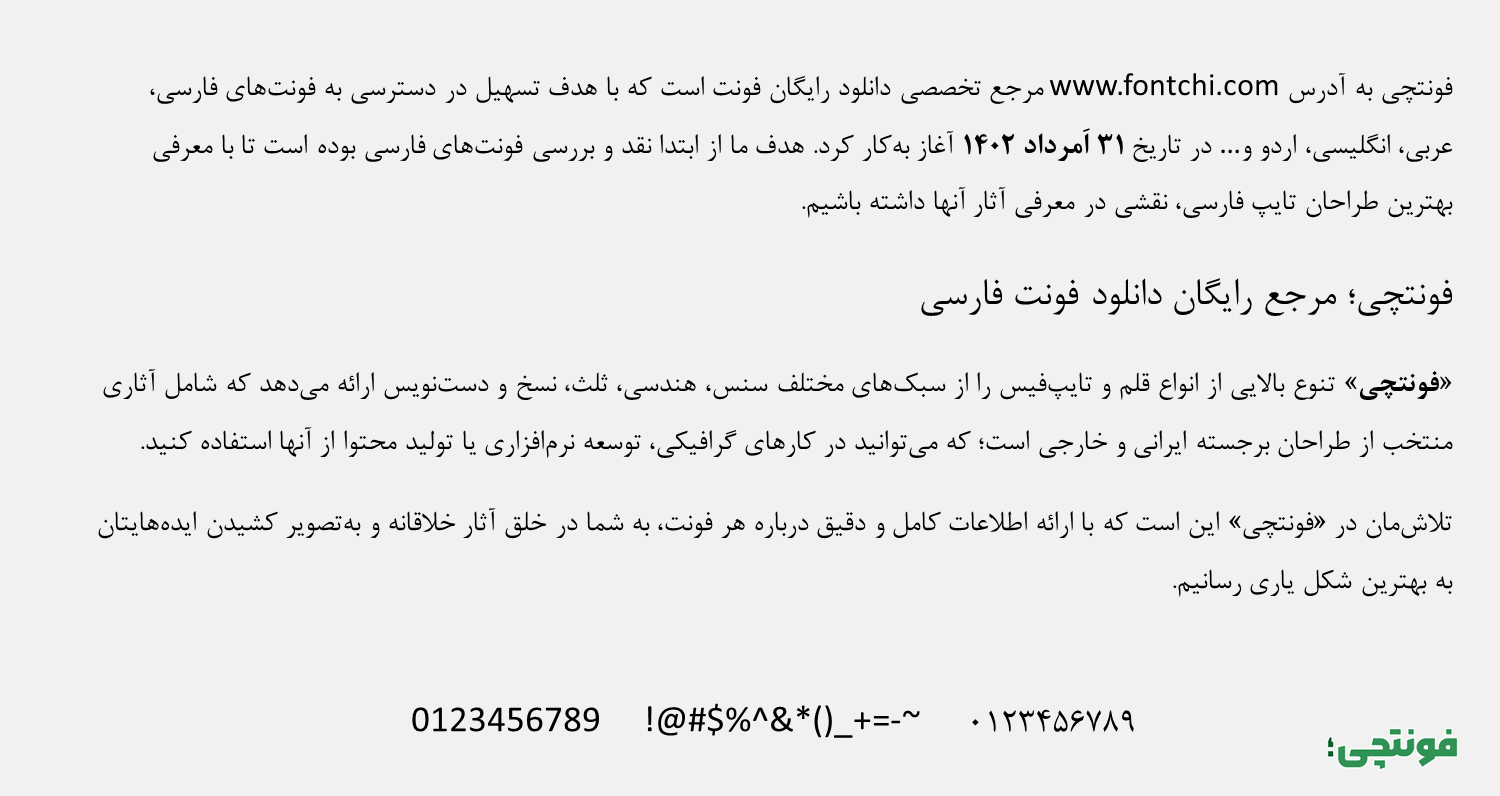
فونت بی نازنین (B Nazanin)
فونت بی نازنین یا فونت ب نازنین (به انگلیسی: B Nazanin) یکی دیگر از فونتهای طراحی شده توسط برنا رایانه است که ساخت آن به دهه ۷۰ برمیگردد. این فونت با خط نسخ طراحی شده که بیشتر در ادارات و سازمانها به عنوان فونت رسمی و اداری مورد استفاده قرار میگیرد. در ادامه این نوشته به لینک دانلود فونت بی نازنین رایگان دسترسی خواهید داشت.
این فونت دارای یک وزن معمولی نرمال است که از دو حالت Regular و Bold پشتیبانی میکند. فونت B Nazanin آخرین آپدیت خود را در سال ۱۳۷۹ دریافت کرده است که نسخه ۲.۰۱ این قلم میباشد.
فونتهای سری بی که فونت B nazanin یکی از محبوبترین آنها است، جزو اولین فونتهای فارسی هستند. این فونتها که در دههای که هنوز خبری از گوشیهای هوشمند نبود و در خانه معدود افراد ایرانی میشد سیستم کامپیوتری یافت طراحی و تولید شدند.
ادارات، سازمانها، شرکتها، مراکز علمی و انتشارات از این فونت بیشترین استفاده را دارند؛ بهطوریکه روزنامهها و مجلات برای متن بدنه اصلی خود یا در نامه نگاریهای اداری از این فونت استفاده میشود. این فونت به قدری امروزه رواج یافته که در پروژههای دانشجویی برخی اساتید استفاده آن را الزامی کردهاند.
در تصویر زیر پیشنمایش این فونت را مشاهده میکنید که حالتهای فارسی، انگلیسی، اعداد فارسی، کاراکترهای خاص و نسخه بولد شده آن را نشان میدهد.
فونت بی نازنین بر اساس خط نسخ طراحی شده است. حروف در آن نسبتا استخوانی هستند و با توجه به طراحی که برای دندانهها، منحنیها، زوایا و چشمیها درنظر گرفته شده است در سایزهای استاندارد قابل خواندن هستند. استفاده از فونت بی نازنین سایز ۱۴ استانداردترین حالت آن است که در نامهنگاریهای رسمی و چاپ روزنامهها نیز مورد استفاده قرار میگیرد.
نقاط در فونت بی نازنین به شکل جدا و لوزی شکل طراحی شدهاند که چنین نقطهگذاری در خط نسخ رایج است. این نقاط به دقت در هر گلیف در جای مناسب قرار گرفته است تا در کلمات و عبارات مختلف باعث بههم ریختگی نگردد.
فونت فارسی b nazanin پشتیبانی کاملی از این زبان دارد و با توجه به اینکه از رسمخط فارسی در زبانهای دیگری مثل عربی، اردو، کردی و ترکی استفاده شده، در کلمات و ترکیباتی که حروف مشترک با زبان فارسی دارند میتوانید از این فونت استفاده کنید. اما بهطور کلی نمیتوان گفت که پشتیبانی از زبانهای دیگر را داشته باشد. چرا که ترکیباتی مثل ««ک، ﮧ، ﮩ، ے» در اردو یا اعداد «۴۵۶» و حروف عربی را در خود ندارد.
خوانایی این فونت در حد طبیعی قرار دارد و همه افراد در سنین مختلف کودک تا بزرگسال میتوانند آن را به راحتی بخوانند. اما باید در نظر داشت که با توجه به سبک طراحی فونت که ساختاری لاغر دارد، برای افرادی که دچار مشکلات بینایی یا ضعف چشم هستند، شاید ضروری باشد از اندازههای بزرگتر از حد معمول استفاده کرد.
فونت b nazanin دارای سبکی است که میتواند برای استفاده در متون کاربردی باشد. برنامههای فوق به شما امکان استفاده از این فونت را خواهند داد. خواه متنی که استفاده میکنید کوتاه باشد یا بلند، این فونت خوانایی و سادگی لازم را برای انتقال محتوا به کاربر دارد.
اگر صفحه اینستاگرامی دارید که از طریق متن نوشته به تولید محتوا میپردازید این فونت میتواند به خوبی امکان خواندن متون را در اندازههای مختلف فراهم کند. از نسخه فونت بی نازنین بولد هم میتوانید در عناوین و تیترها استفاده کنید.